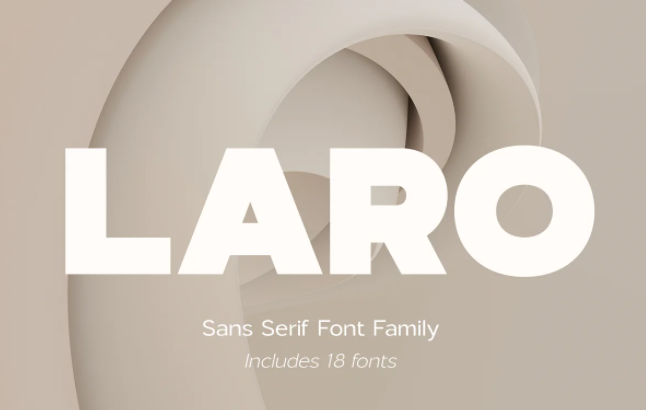
Laro - это современный шрифт sans-serif, включающий девять начертаний от тонкого до черного и девять начертаний в стиле Italic.
Этот многоцелевой шрифт захватывает огромный диапазон для дизайна и создания вашего проекта. Laro прекрасно справится с самыми разными задачами, при этом он всегда будет выглядеть стильно и современно. С его помощью можно создавать логотипы, этикетки, использовать в рекламе, упаковке, брендинге, обложках книг и журналов, косметике, баннерах, плакатах, заголовках, описаниях и многом другом. Этот шрифт прост в использовании, имеет функции OpenType.